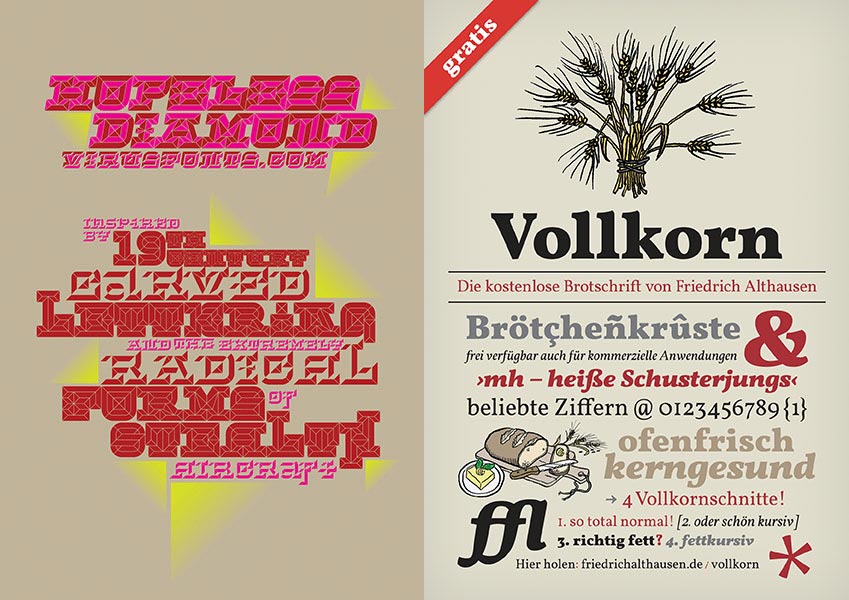
Vom 10. März bis 5. Mai 2013 zeigt die Ausstellung »Schrift im 21. Jahrhundert« im Museum für Druckkunst Leipzig Einblicke in zeitgenössische Schriftgestaltung. Rund 110 Positionen aktueller Schriftdesigns aus über 14 Ländern sind in der zweiteiligen Ausstellung vereint.
Der erste Teil der Ausstellung präsentiert die aus England übernommene Ausstellung »Types for the New Century. An Exhibition of contemporary type design and typography«. Die von Will Hill (Anglia Ruskin Universität, Cambridge, UK) kuratierte Ausstellung macht nach Stationen in London, Bristol und Birmingham nun Halt in Leipzig und stellt rund 90 Schriftgestalter mit ihren Entwürfen aus den letzten zwölf Jahren vor. Damit blickt die Ausstellung auf die erste Dekade des neuen Jahrtausends und stellt aktuelle Tendenzen in der internationalen Typografieszene vor. Vertreten sind Schriftbeispiele von renommierten Gestaltern wie Martin Majoor, Jonathan Barnbrook und Matthew Carter sowie von jüngeren Schriftdesignern.
Das typografische Schaffen in Mitteldeutschland fokussiert der zweite Ausstellungsteil mit rund 20 Positionen aus Kunsthochschulen der drei Bundesländer Thüringen (Bauhaus-Universität Weimar), Sachsen-Anhalt (Burg Giebichenstein Kunsthochschule Halle/Saale) und Sachsen (Hochschule für Grafik und Buchkunst Leipzig). Gezeigt werden neue, teils unveröffentlichte Schriften aus den letzten fünf Jahren sowie deren praktische Anwendung in analogen und digitalen Medien. Weitere Informationen auf der Presseseite des Museums …
Das Thema der Ausstellung wird im Rahmen der 19 Leipziger Typotage am 27. April 2013 in Vorträgen aufgegriffen. Acht Referenten, darunter Tim Ahrens (Berlin), Friedrich Forssmann (Kassel) und Henning Skibbe (Hamburg), diskutieren im Museum für Druckkunst Leipzig über Gegenwart und Zukunft von Schrift und Typografie.
Abbildungen: Jonathan Barnbrook: Hopeless Diamond, Friedrich Althausen: Vollkorn